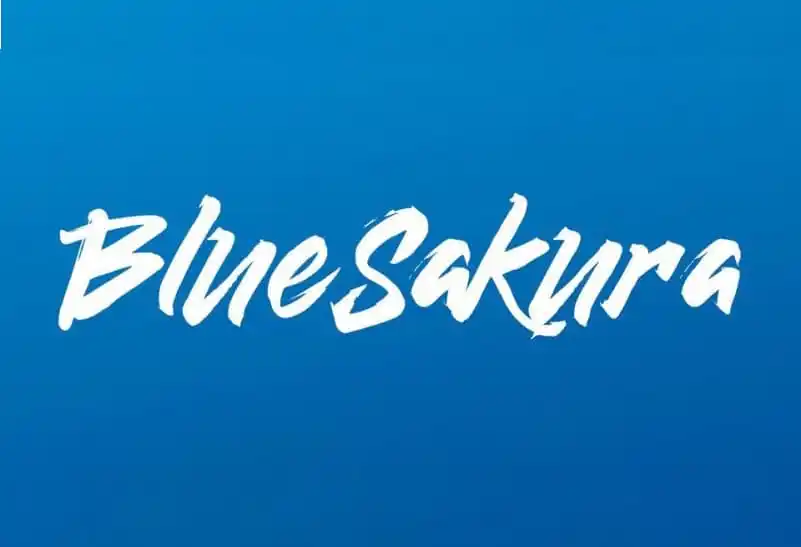
BlueSakura Brush Font – Fonte Grátis
BlueSakura Brush Font
A BlueSakura Brush Font é uma fonte criada por Haris Prawoto que captura a essência dos desenhos artesanais. Com seu traço natural e áspero, esta fonte tem um toque bold e forte. Ideal para projetos de marca, logotipos, designs de casamentos, posts nas redes sociais, anúncios, embalagens de produtos, design de produto, etiquetas, fotografia e até mesmo marcas de água. É uma escolha perfeita para qualquer projeto que busque a delicada textura da escrita livre. Com certeza é um recurso gráfico convidativo que dará um toque único ao seu trabalho.